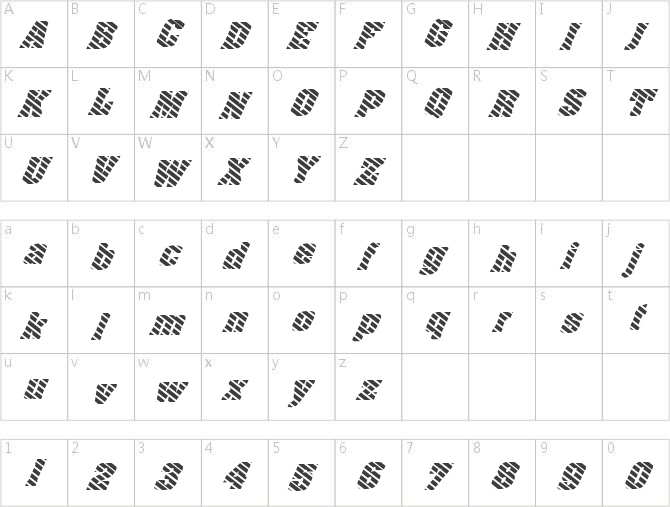
FZ BASIC 52 STRIPED ITALIC
FZ BASIC 52 STRIPED ITALIC介紹
FZ BASIC 52 STRIPED ITALIC字體字庫是一款讓人賞心悅目、百看不厭的英文字體,適合各類廣告和產品包裝設計應用,字體大小0.07MB,格式為ttf字體,上傳用戶是瓜皮,作者/版權方為未知